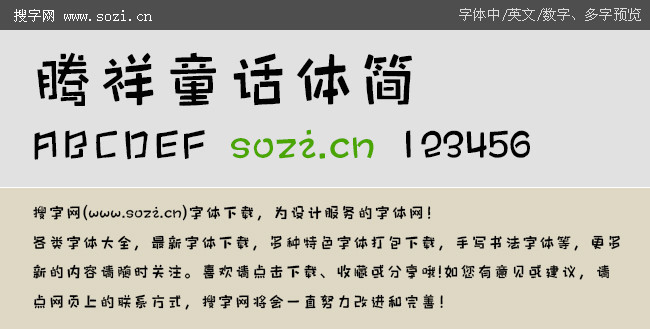
騰祥童話體簡
搜字網(wǎng)提供一款騰祥童話體簡中文字體下載,騰祥童話體簡字體是一款由騰祥字庫全新開發(fā)的常規(guī)簡體中文字體,該字體筆畫粗細(xì)適度且錯落有致,筆畫與筆畫之間適度留白形成疊壓使字體看起來更清晰,增強(qiáng)可讀性。結(jié)構(gòu)夸張隨性,但又有一定之規(guī),歪斜的筆畫以筆畫與筆畫間的協(xié)調(diào)為根本,,能夠適用于藝術(shù)設(shè)計、包裝印刷、簽名設(shè)計、圖形設(shè)計等領(lǐng)域。(此款為個人非商用版,如需商用請聯(lián)系騰祥字庫購買)